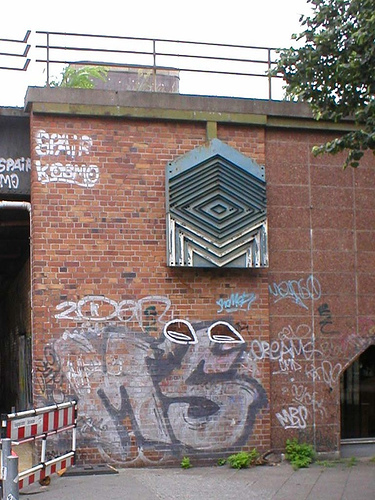
Buchstabenmuseum
Ist noch in der Aufbauphase und such wohl Exponate. Schönes Vohaben :D
Das Wort NEULETTER auf der Website schreckt mich ab, mich näher mit einer Mitgliedschaft zu befassen, obwohl ich das ganze Vorhaben positiv sehe.
Aber wahrscheinlich verstehe ich in meinem fortgeschrittenen Alter manches nicht mehr.
… NEULETTER …
Ging mir ebenso, ich denke aber dass das ein sehr mühsamer Witz hätte sein sollen.
Wenn sie's ja wenigstens Letter News genannt hätten ... Dann müsste man zumindest nicht insgeheim befürchten, es handele sich um einen besonders seltsamen Übersetzungsfehler ...
Freut euch lieber über die schönen Exponate, statt hier immer nur rum zu meckern! :hammer:
Nur mal stellvertretend für etliche andere Berliner Schätze:
Da werden doch Erinnerungen wach! *schwelg*
Ja klar, war nur ein Egomanieanfall meinerseits nach dem zweiten Glas Wein. Habe übrigens vorher schon lange gerätselt, was das M wohl mal zu bedeuten gehabt hat. Nun ist aber außer der Zentralmarkthalle auch das schöne Schild weg.